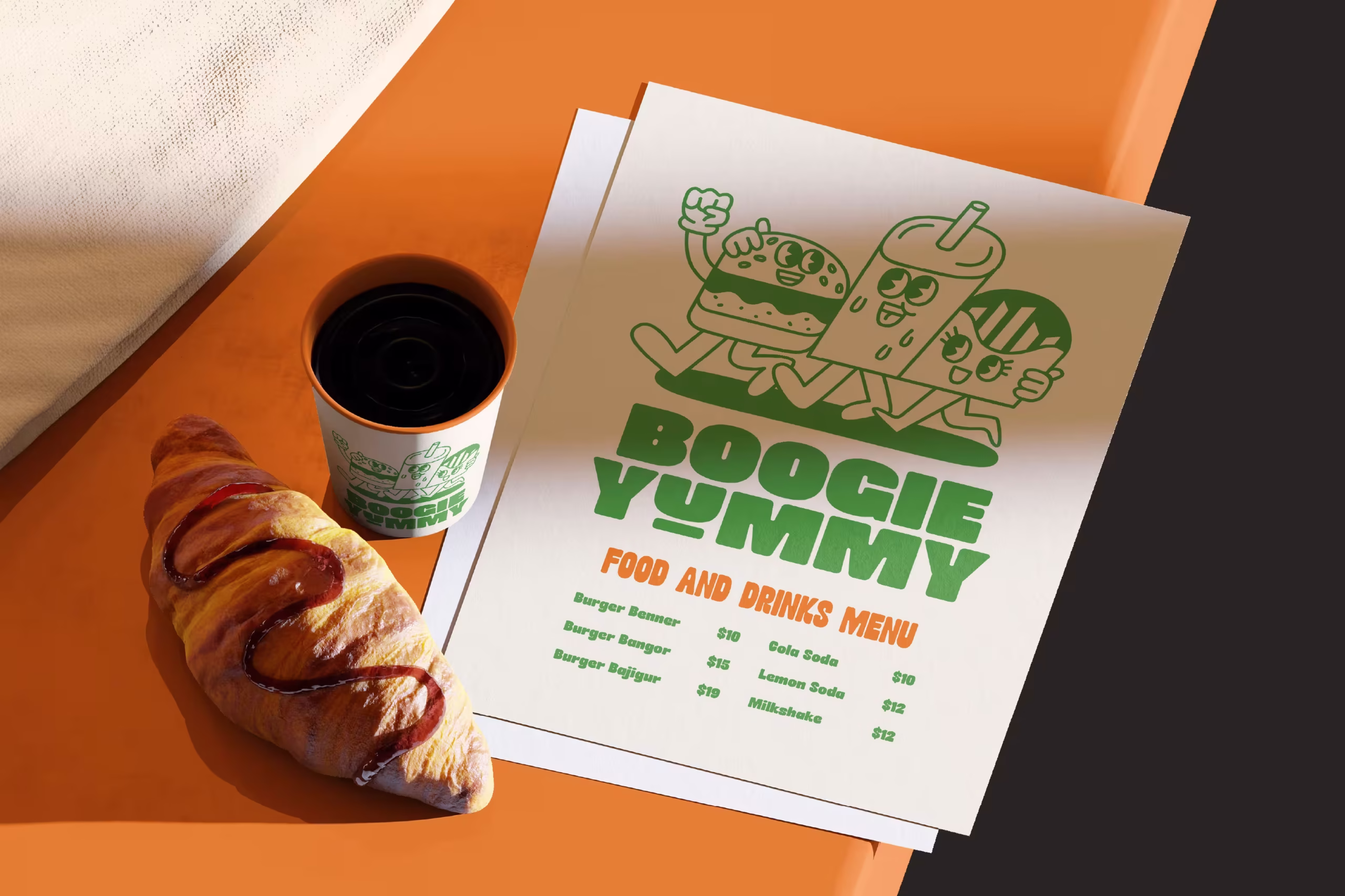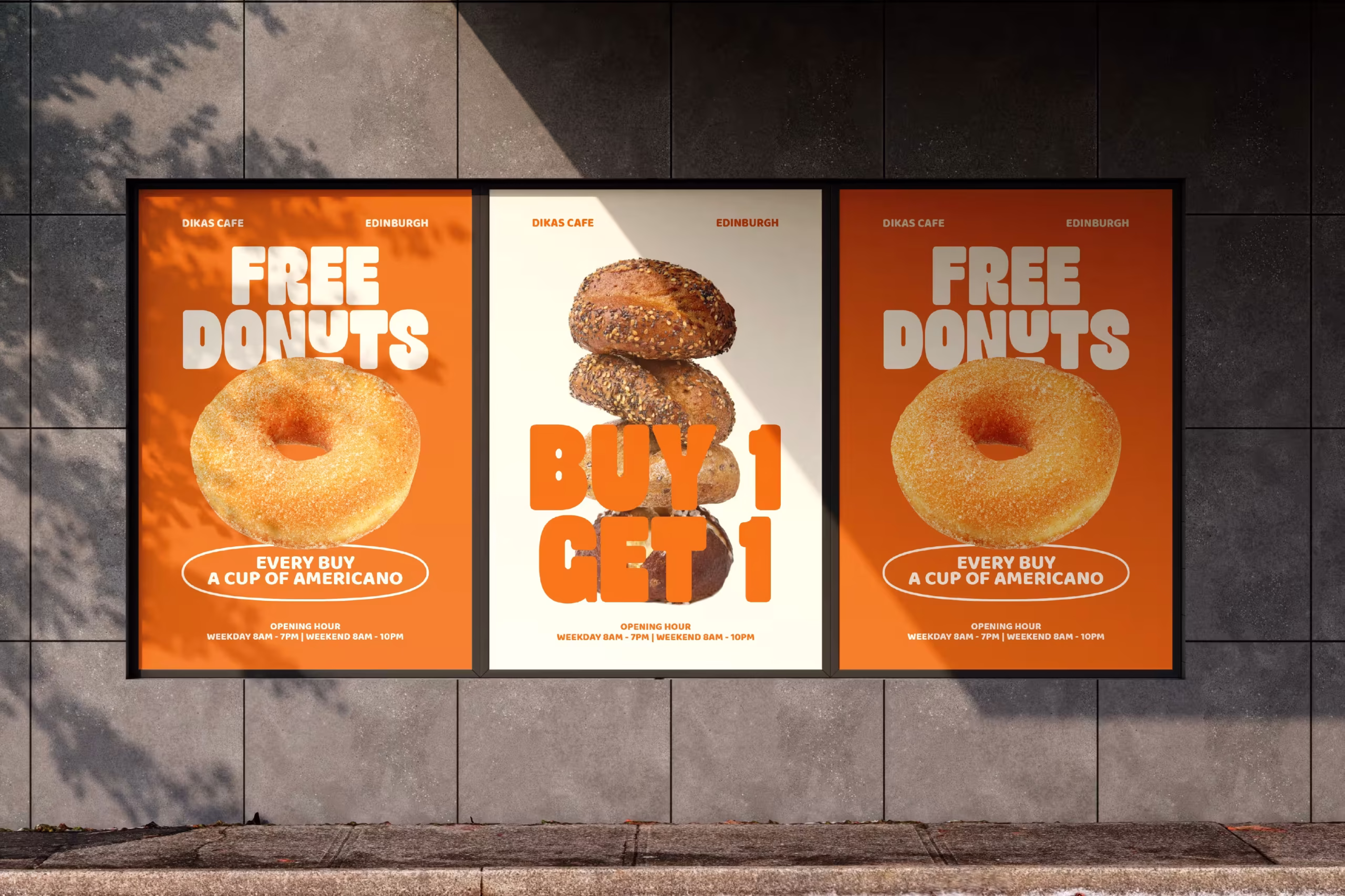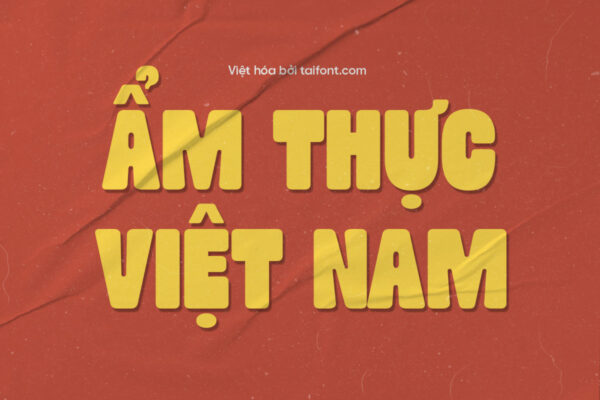
Giới thiệu về Font TF Groovezilla Regular & Italic Việt hóa
TF Groovezilla Regular & Italic Việt hóa là một bộ font chữ nổi bật với thiết kế to lớn, tròn trịa và đầy đặn, mang đến vẻ ngoài vui tươi, năng động và cực kỳ nổi bật. Font này gợi cảm giác về sự đầy đặn, tươi mới và một chút hoài niệm, lý tưởng để tạo điểm nhấn độc đáo và thu hút mọi ánh nhìn, đặc biệt trong các thiết kế ẩm thực hoặc poster quảng cáo quy mô lớn.
Với đặc điểm là hình dáng tròn mềm mại, nét chữ to đậm và tính thẩm mỹ cao, Groovezilla là lựa chọn hoàn hảo cho các thiết kế muốn truyền tải sự ngon miệng, ấm cúng và gần gũi:
- Thiết kế ẩm thực: Hoàn hảo để sử dụng trên menu, bao bì sản phẩm, poster quảng bá món ăn, hoặc các ấn phẩm truyền thông của nhà hàng, quán ăn, quán cà phê. Font này giúp món ăn trở nên hấp dẫn hơn, tạo cảm giác ngon miệng và thu hút sự chú ý của thực khách.
- Thiết kế poster lớn: Lý tưởng để tạo các tiêu đề chính (headline), slogan, hoặc thông điệp quảng cáo trên poster, banner, hoặc bất kỳ ấn phẩm nào cần sự chú ý tối đa. Nét chữ to và đậm của font giúp thông điệp của bạn nổi bật, dễ đọc và truyền tải một cách hiệu quả ngay từ cái nhìn đầu tiên.
- Thiết kế bao bì sản phẩm: Phù hợp để sử dụng trên nhãn mác, bao bì của các sản phẩm thực phẩm, đồ uống, bánh kẹo, hoặc các sản phẩm có phong cách vui tươi. Font này giúp sản phẩm trở nên nổi bật và thu hút.
- Thiết kế logo và nhận diện thương hiệu: Có thể dùng cho logo hoặc bộ nhận diện thương hiệu của các công ty, doanh nghiệp trong lĩnh vực ẩm thực, giải trí, hoặc các sản phẩm mang tính đột phá và hướng tới giới trẻ.
Với TF Groovezilla Regular & Italic Việt hóa, bạn có thể dễ dàng thổi hồn vui tươi, sự ngon miệng và vẻ đẹp độc đáo vào các thiết kế, tạo ra những sản phẩm không chỉ đẹp mắt mà còn đầy cảm xúc và sức hút đặc biệt.